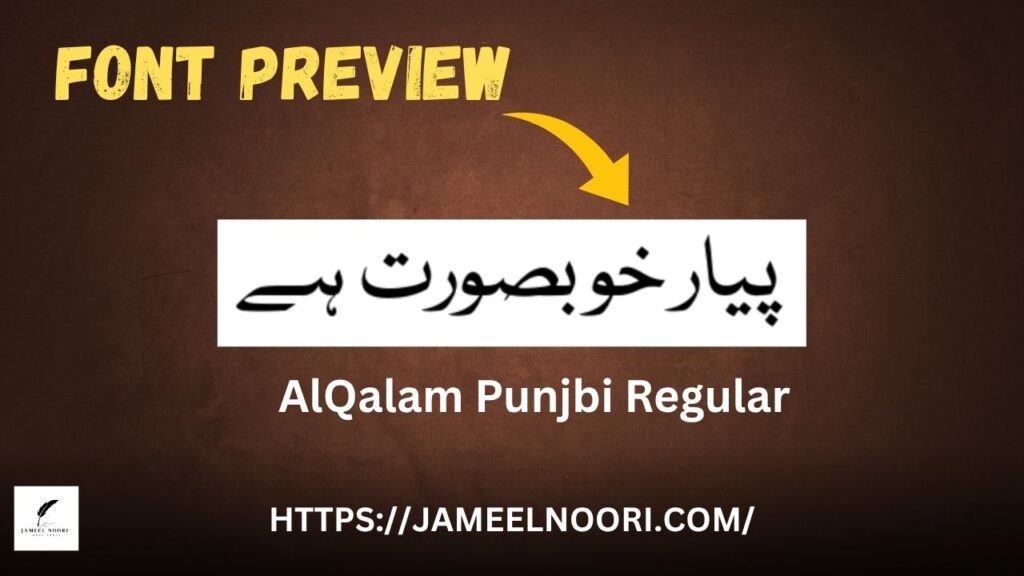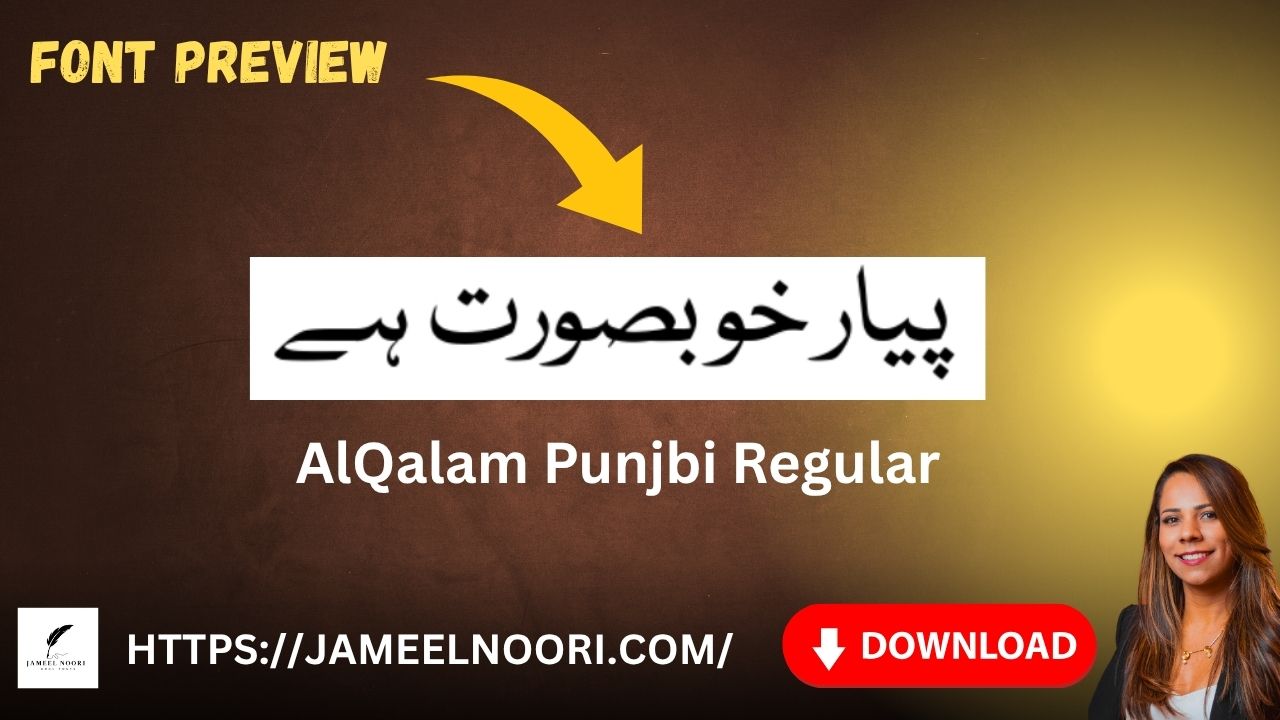
Introduction – AlQalam Punjbi Regular
Agar aap stylish aur readable Urdu ya Punjabi text likhne ke liye ek khoobsurat font dhoondh rahe hain, to AlQalam Punjbi Regular font aap ke liye best choice ho sakta hai. Yeh ek TrueType Urdu Font hai jo na sirf design mein elegant hai balkay readability mein bhi behtareen hai. Is article mein hum detail se dekhein ge ke AlQalam Punjbi Regular font kya hai, isay kaise download karein, iska character map aur features kya hain, aur yeh font kin platforms pe use kiya ja sakta hai.
Font Overview – AlQalam Punjbi Regular
| Glyphs | Standard Urdu/Punjabi letters |
Why Choose AlQalam Punjbi Regular Font?
- ✅ Stylish Design – Elegant strokes aur smooth kerning.
- ✅ Urdu aur Punjabi ke liye Perfect – Dono zabanon ke native letters ka support.
Where You Can Use This Font
- ✔ Urdu & Punjabi Poetry
- ✔ Wedding & Event Cards
- ✔ Quranic Verses (Naqsh Style)
- ✔ Social Media Posts in Roman Urdu
Kya yeh font Urdu aur Punjabi dono support karta hai?
Jee haan, yeh font Urdu aur Punjabi ke native characters ko properly render karta hai.
Yeh font kis style mein likhta hai?
Yeh font Regular Style mein likhta hai jo casual aur readable hota hai.